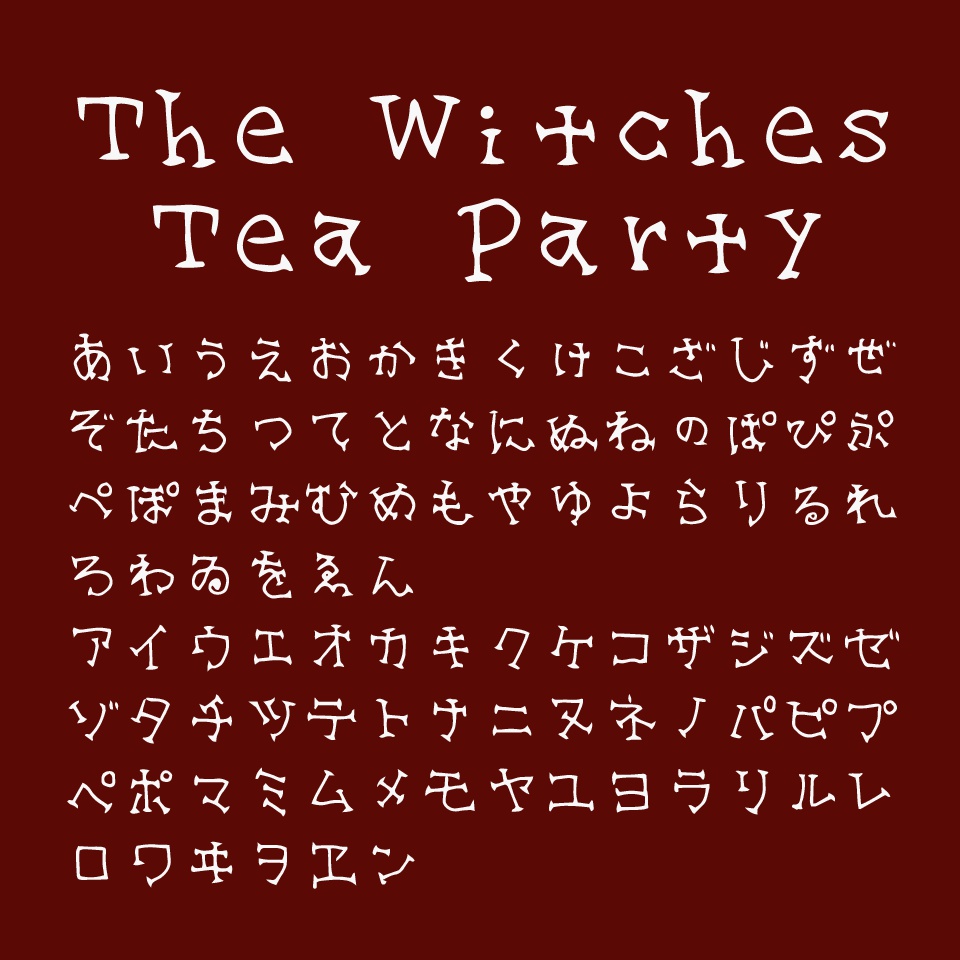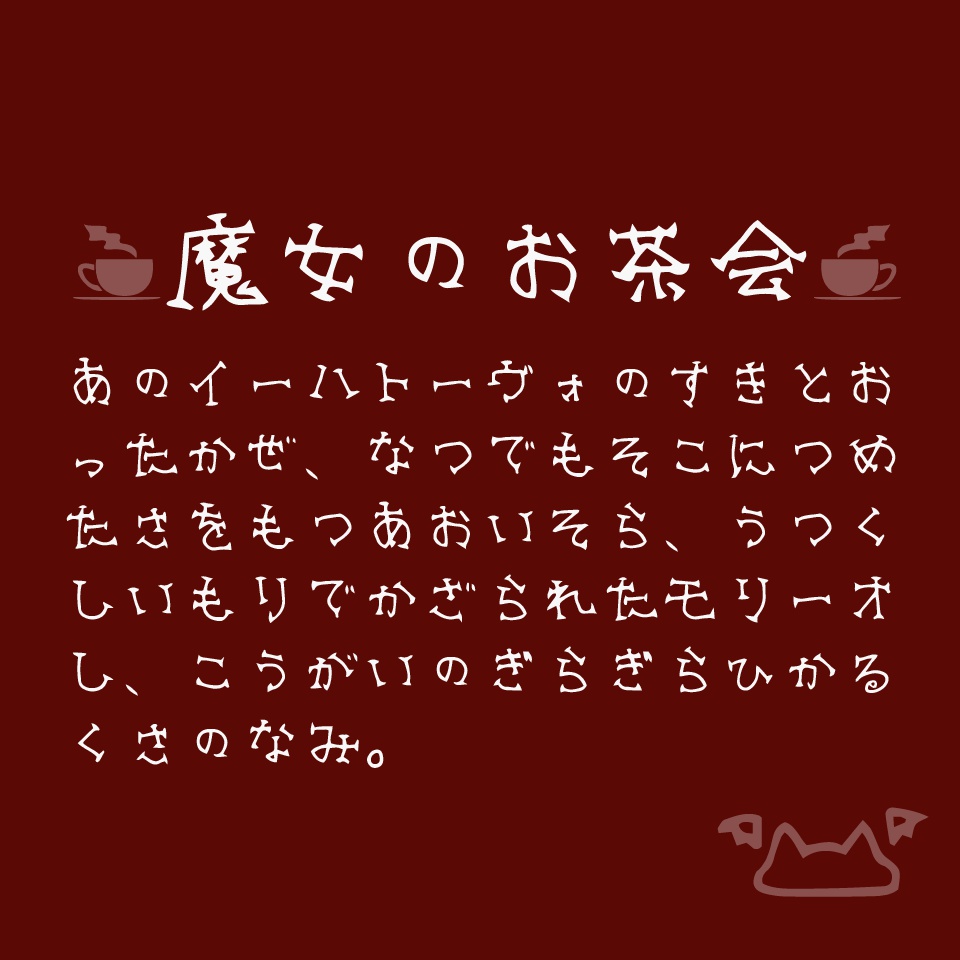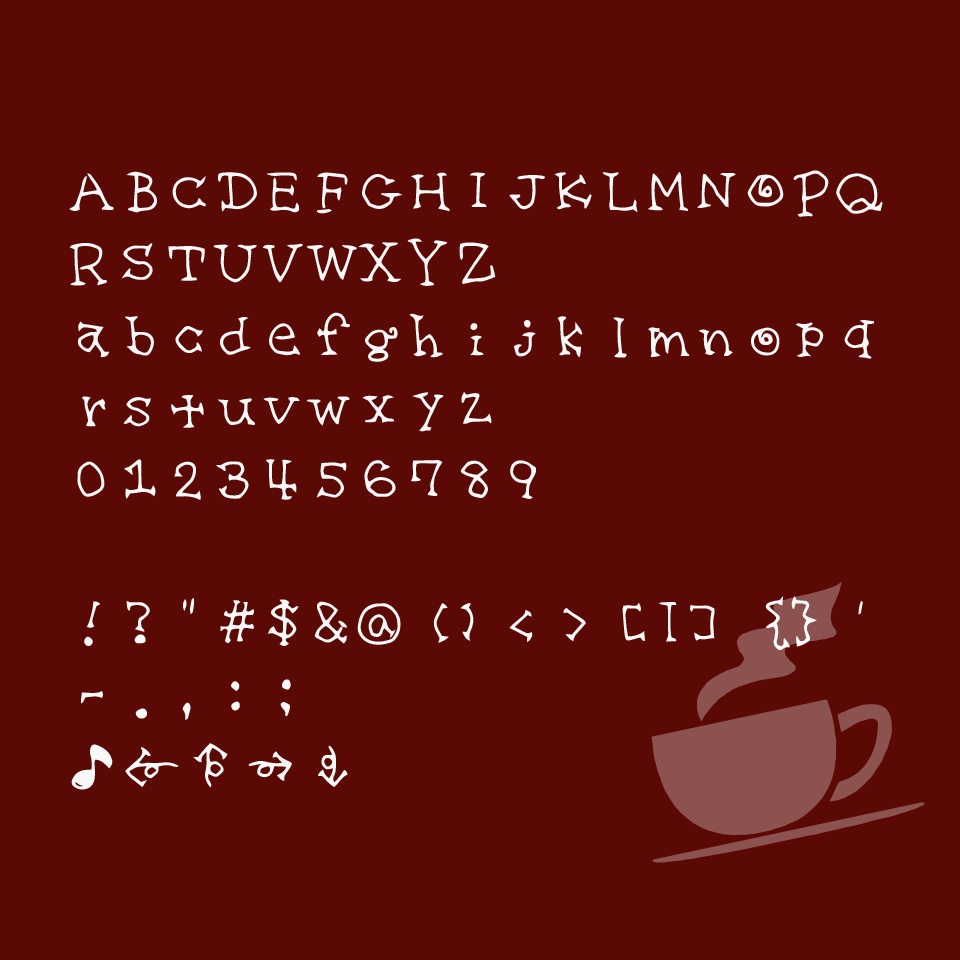
魔女のお茶会フォント The Witches Tea Party
魔女のお茶会をイメージしたフォントです。ハロウィンやホラー系に使いやすいと思います。 英数字・ひらがな・カタカナ・一部記号を収録しています。 漢字は「魔女茶会」が使えます。 全角・半角の区別はありません。どちらでも同じ文字が出力されます。